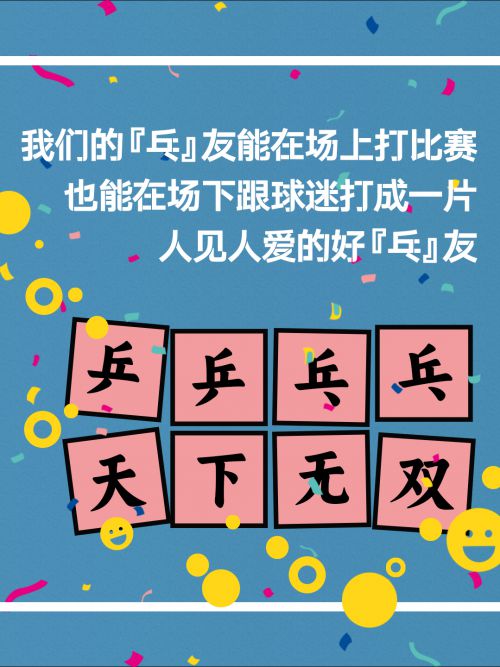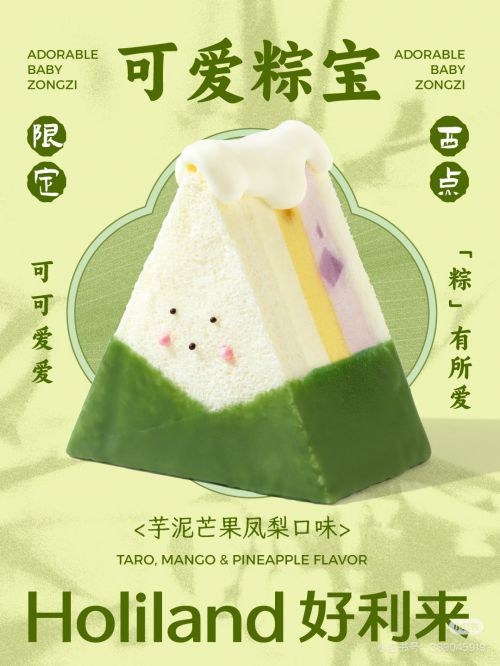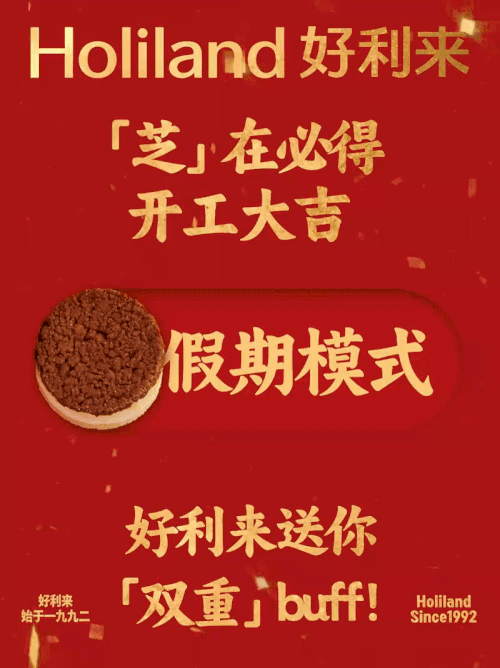
阿里妈妈东方大楷
### 阿里妈妈东方大楷:传承颜体风骨的免费商用楷体字体 阿里妈妈东方大楷是一款融合传统韵味与现代设计需求的楷体字体,以中国风古典美学为核心风格,支持简体中文常规字符集,提供免费商用授权。字体灵感源自颜真卿《多宝塔碑》,通过算法生成与人工精修结合,既保留颜体丰腴厚重的笔法精髓,又优化了数字时代的应用体验。 字形方正稳健,重心居中平衡,中宫宽博舒展,展现出端庄大气的视觉张力。笔画设计以直角起收,粗细均匀有力,方头笔触搭配清晰的笔画断开结构,还原了书法中落笔藏锋、转笔护尾的书写韵味,整体呈现饱满圆融、浑厚沉稳的艺术效果。 作为免费商用字体,阿里妈妈东方大楷适用于海报标题、品牌标识、文化宣传品等场景,其兼具传统书法底蕴与现代设计规范的特性,能为各类创意项目注入浓厚的东方美学气息。